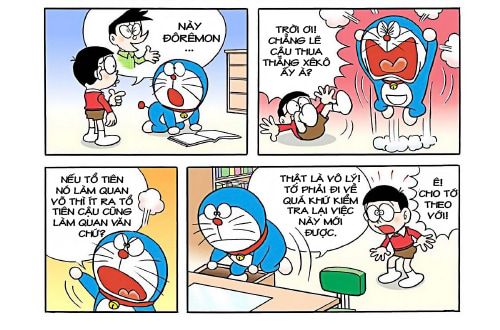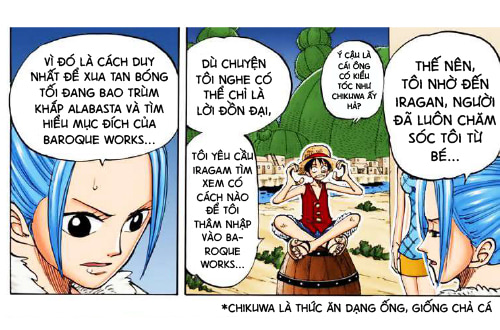
Font chữ truyện tranh việt hóa đầy đủ mới nhất
Khám phá thế giới truyện tranh Việt hóa với bộ sưu tập font chữ đầy đủ và mới nhất. Bài viết này sẽ giới thiệu cho bạn những font chữ truyện tranh được cập nhật liên tục để đáp ứng nhu cầu đa dạng của cộng đồng yêu truyện tranh. Cá Mập sẽ hướng dẫn bạn cách sử dụng và tận dụng những font chữ này để tạo ra những tác phẩm truyện tranh độc đáo và ấn tượng nhất. Trong bài viết này, chúng ta sẽ tìm hiểu về một số bộ font chữ truyện tranh Việt hóa đầy đủ mới nhất.
Font chữ truyện tranh HL Comic Việt hóa - Nét chữ mềm mại, đa dạng
Font chữ truyện tranh HL Comic Việt hóa
Chúng ta đã biết về tác giả Hùng Lân, người đã tạo ra bộ font chữ VNI-HLThuphap và VNI-OngDoHL nổi tiếng, được sử dụng rộng rãi. Nhưng vẫn còn một bộ font chữ khác của Họa sĩ Hùng Lân mà bạn nên biết, đó là bộ font truyện tranh HL Comic Việt hóa, một sáng tạo độc đáo của ông sử dụng bảng mã Unicode.
Tác phẩm này ban đầu chỉ hỗ trợ bảng mã BK HCM2 và VNI và có chỉ 3 font chữ. Tuy nhiên, sau đó, để đảm bảo tính tương thích trên nhiều thiết bị và hệ điều hành, các họa sĩ đã chuyển sang sử dụng bảng mã Unicode quốc tế.
Bộ font chữ này có tiền tố HL và hậu tố Uni hoặc Unicode điển hình, mang lại sự linh hoạt cho việc điều chỉnh kích thước để phục vụ cho mọi mục đích của bạn.
Dưới đây là một số ưu điểm và nhược điểm của font HL Comic Việt hóa:
Ưu điểm:
• Thích hợp cho Truyện Tranh: Font chữ này rất thích hợp để nhập các lời thoại nhân vật hoặc lời độc thoại trong truyện tranh, giúp tạo nên bản vẽ thú vị hơn.
• Nét Chữ Mềm Mại: Đặc điểm của font HL Comic là nét chữ mềm mại, không thô cứng, giúp tạo nên sự hài hòa trong truyện tranh.
• Tương Thích Rộng Rãi: Bởi vì font chữ này được mã hóa bằng Unicode, nó tương thích với hầu hết các thiết bị và hệ điều hành phổ biến như Windows, macOS và Linux.
Nhược điểm:
• Không Hỗ Trợ Hiệu Ứng Đặc Biệt: Font HL Comic không phù hợp để tạo các hiệu ứng đặc biệt trong văn bản, nên nếu bạn cần sử dụng hiệu ứng đặc biệt, bạn có thể phải tìm kiếm các font chữ khác.
• Hạn Chế Số Lượng Font: Do đây là một dự án cá nhân, bộ font chỉ có 3 font chữ, không đa dạng như một số bộ font chữ lớn khác.
• Không Tương Thích với Bảng Mã Thông Thường: Font chữ này không hoạt động với các bảng mã thông thường và yêu cầu sử dụng mã hóa riêng của nó, điều này có thể tạo ra sự bất tiện trong một số trường hợp.
Tóm lại, font HL Comic Việt hóa là một lựa chọn thú vị cho các người sáng tạo trong lĩnh vực truyện tranh, với nét chữ mềm mại và tính tương thích cao với nhiều thiết bị. Tuy nhiên, nó có nhược điểm của mình và cần xem xét kỹ trước khi sử dụng cho các dự án cụ thể.
Font chữ truyện tranh Teddy Bear -  Lựa chọn tối ưu cho hiệu ứng đặc biệt và sáng tạo trong Comic và Manga
Font chữ truyện tranh Teddy Bear
Nếu bạn đã đọc nhiều truyện tranh, bạn sẽ gặp font chữ Việt hóa "Teddy Bear" ít nhất một lần trong đời. Điều đặc biệt về truyện tranh là cách câu thoại và văn bản câu chuyện được trình bày. Vì vậy, khi bạn bắt đầu viết hoặc sáng tác truyện tranh, bạn cần biết rằng font chữ truyện tranh chuyên dụng là gì.
Với môi trường đặc biệt của truyện tranh, nơi cần có một khoảng trống nhỏ để viết chữ, font chữ phải dễ đọc, gần gũi và không nên quá nghiêm túc. Nếu nét chữ quá đẹp, nó có thể không phù hợp với không gian hẹp màu trắng.
Font chữ "Teddy Bear" được biết đến là một font truyện tranh Việt hóa dựa trên bảng mã Unicode chuẩn quốc tế, vì vậy nó tương thích với hầu hết các thiết bị và hệ điều hành hiện nay. Tuy nhiên, hãy nhớ rằng khi bạn tải font chữ truyện tranh này và sử dụng nó, bạn chỉ được phép dùng cho mục đích cá nhân, không phải mục đích thương mại.
Đối tượng mà font chữ "Teddy Bear" hướng tới chính là người làm truyện tranh comic và manga. Bộ font chữ này bao gồm hơn 100 font Teddy Bear, được thiết kế để tối ưu cho việc tạo ra comic, blambot, và hỗ trợ việc gõ tiếng Việt theo bảng mã Unicode.
Dưới đây là một số ưu điểm và nhược điểm của font chữ "Teddy Bear":
Ưu điểm:
• Thích hợp cho hiệu ứng đặc biệt: Font chữ này rất thích hợp khi bạn muốn tạo ra các hiệu ứng đặc biệt trong văn bản của bạn.
• Tương thích rộng rãi: Vì sử dụng mã hóa Unicode, font chữ này tương thích với hầu hết các thiết bị và hệ điều hành phổ biến như Windows, macOS và Linux.
• Miễn phí và dễ cài đặt: Font chữ này hoàn toàn miễn phí cho mục đích cá nhân và cài đặt nó cũng khá đơn giản.
• Cập nhật thường xuyên: Do có nhiều nhóm đang sử dụng font chữ Teddy Bear, nên nó thường xuyên được cập nhật để sửa lỗi và cải thiện chất lượng, đảm bảo người dùng yên tâm.
Nhược điểm:
• Không phù hợp cho lời nói bình thường: Font chữ Teddy Bear không thích hợp để viết lời thoại bình thường của nhân vật trong bóng thoại, nó thường được sử dụng để tạo hiệu ứng đặc biệt.
• Font chữ đồng nhất: Các font chữ trong bộ này có thể trông rất giống nhau, không tạo sự đa dạng trong việc trình bày văn bản.